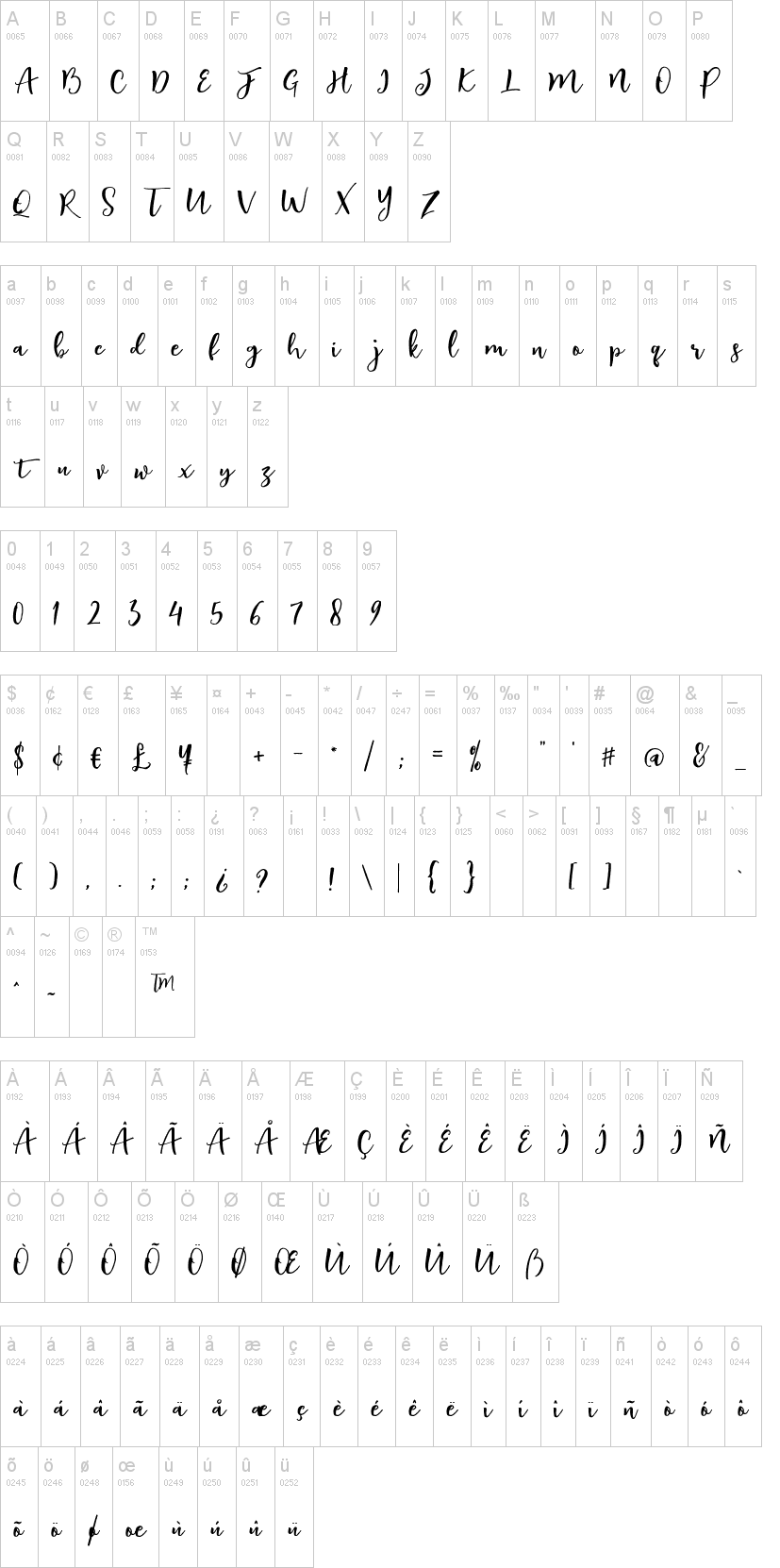
Artlove 字体是一种优美的手写字体,适合用于多种场合,如海报设计、手写信件、个人博客等。它的字形流畅、优美、充满艺术感,字母之间的间距适中,整体看上去非常和谐。 Artlove 字体具有多种字重,包括 Light、Regular、Bold 等等,可以根据需要选择合适的字重来使用。此外,Artlove 字体还支持多种语言,包括英语、西班牙语、法语、德语、意大利语等等。 总的来说,Artlove 字体是一款精美的手写字体,适合用于多种设计场合,能够给设计作品带来浓厚的艺术气息。内容介绍
Artlove是一款非常不错的手写艺术字体,具有很好的视觉感,适合于文化类的宣传设计、商业类品牌的广告和产品包装设计以及个性化文字排版等较多场景。